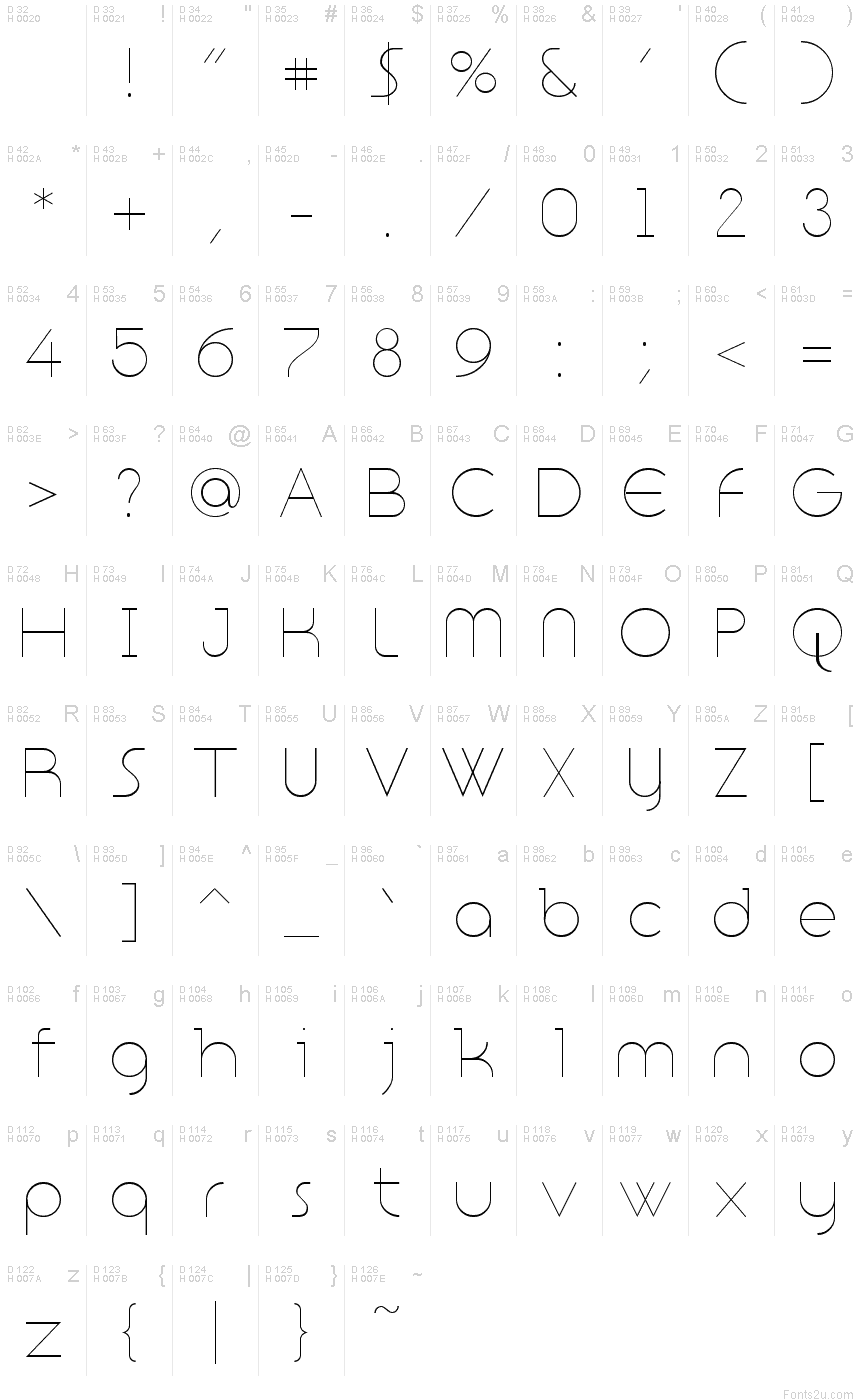
Resselle, stworzona przez Andy Kennedy, to darmowy retro displayowy krój sans serif o bardzo cienkich liniach, szerokich okrągłych formach i czystych geometrycznych połączeniach. Jej płynne krzywe przywodzą na myśl dopracowane liternictwo z lat 70. XX wieku.
Branding modowy i oprawa graficzna albumów mogą wydawać się odległe, ale oba te obszary korzystają z jej zgrabnych proporcji i stylistyki epoki, zwłaszcza w logotypach czy wyrazistych napisach na okładkach eleganckich wydawnictw i wytwórni. Może także nadać kształt zaproszeniom, opakowaniom kosmetyków i szyldom butików w dopracowanym stylu vintage, w którym niemal monolinearna konstrukcja staje się częścią szerszego motywu graficznego w stylu Art Deco lub późnego modernizmu.